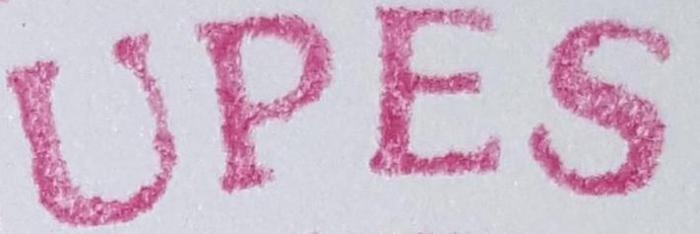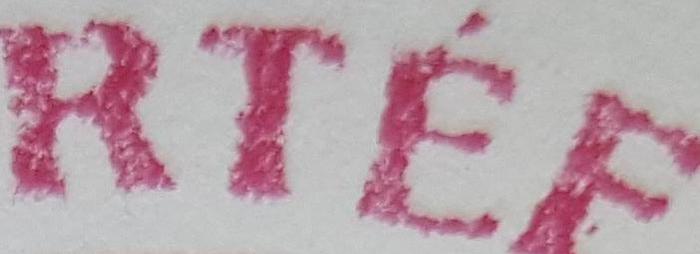
ich heiße Sascha, ich bin neu hier. Leute, ich brauche eure Hilfe. Kann mir einer von euch verraten um welcher Schriftart handelt es sich hier?
Könnte man das ganze Gebilde (Rundsiegel?) sehen?
An die Souvenir musste ich auch als erstes denken, aber das untere R? ... Korinna oder Benguiat sind's jedenfalls nicht, die kamen mir auch noch in den Sinn ...
Könnte man das ganze Gebilde (Rundsiegel?) sehen?
[…] denken lassen. Aber die Buchstaben sind dermaßen zerfressen – das ist ein ziemliches Rätselraten.
[…] in den Sinn ...
Falls es sich tatsächlich um irgendeine Form eines Rundsiegels (bzw. im deutschländischen Sprachgebrauch: eines Rundstempels) handelt, käme mir hier folgendes als erstes in den Sinn: http://www.typografie.info/3/topic/35010-was-könnte-das-denn-sein/
Eine Arial wie in dem verlinkten thread #35010 ist es mit Sicherheit nicht.
Ich glaube die Anspielung ging dahingehend, dass es sich hier evtl. um ein Siegel handelt, bei dessen Nachbau man keine Beihilfe leisten sollte – wie im Link die eventuelle Fälschung einer Rechnung. :tuschel:
Hätte man auch genau so gesagt haben können, wenn man sich denn konkret äußern würde ...  ;-)
Da jeder Mensch einen Rundstempel anfertigen lassen kann und diese nicht grundsätzlich offiziellen Charakter haben müssen, weiß ich nicht ob das hier wirklich relevant ist.
Die üblichen Fragen, wo kommt das her und wie alt ist die Vorlage, fände ich schon interessant um gewisse technische Überlegungen mit einfließen lassen zu können. Könnte es z. B. sein, dass die Abweichungen von der Souvenir von einem fototechnischen Rundsatz kommen? Wurde vielleicht ein Nachbau der Souvenir verwendet? Beides könnte man schon an Hand der Entstehungszeit evtl. ausschließen oder vermuten ...
… Hätte man auch genau so gesagt haben können …
Wäre fürs Verständnis hilfreich gewesen, ja. ;-)